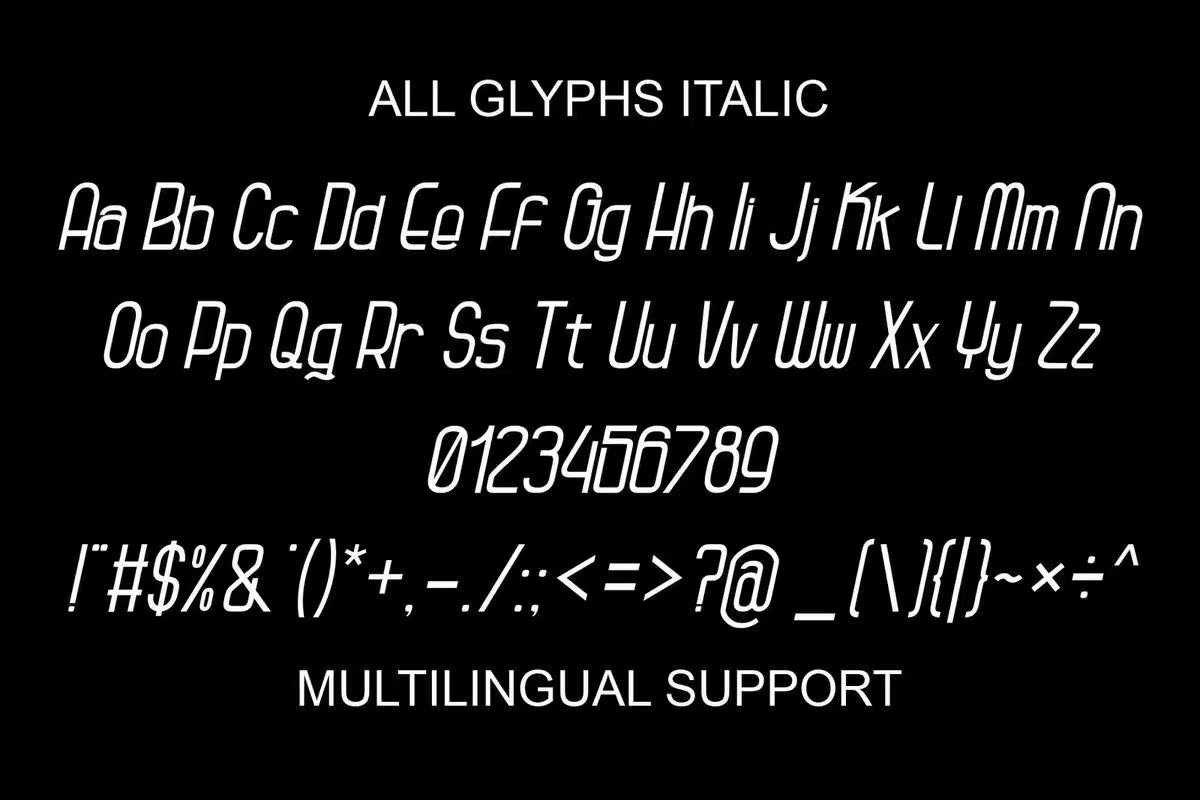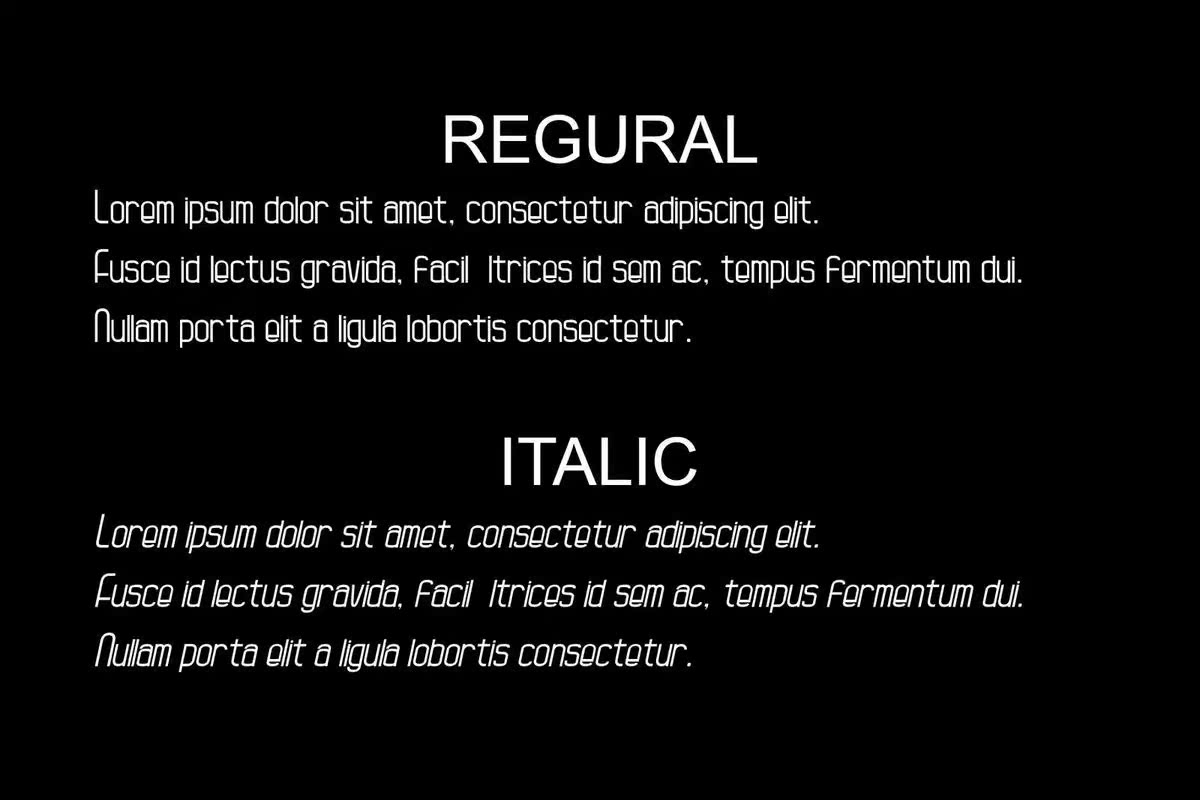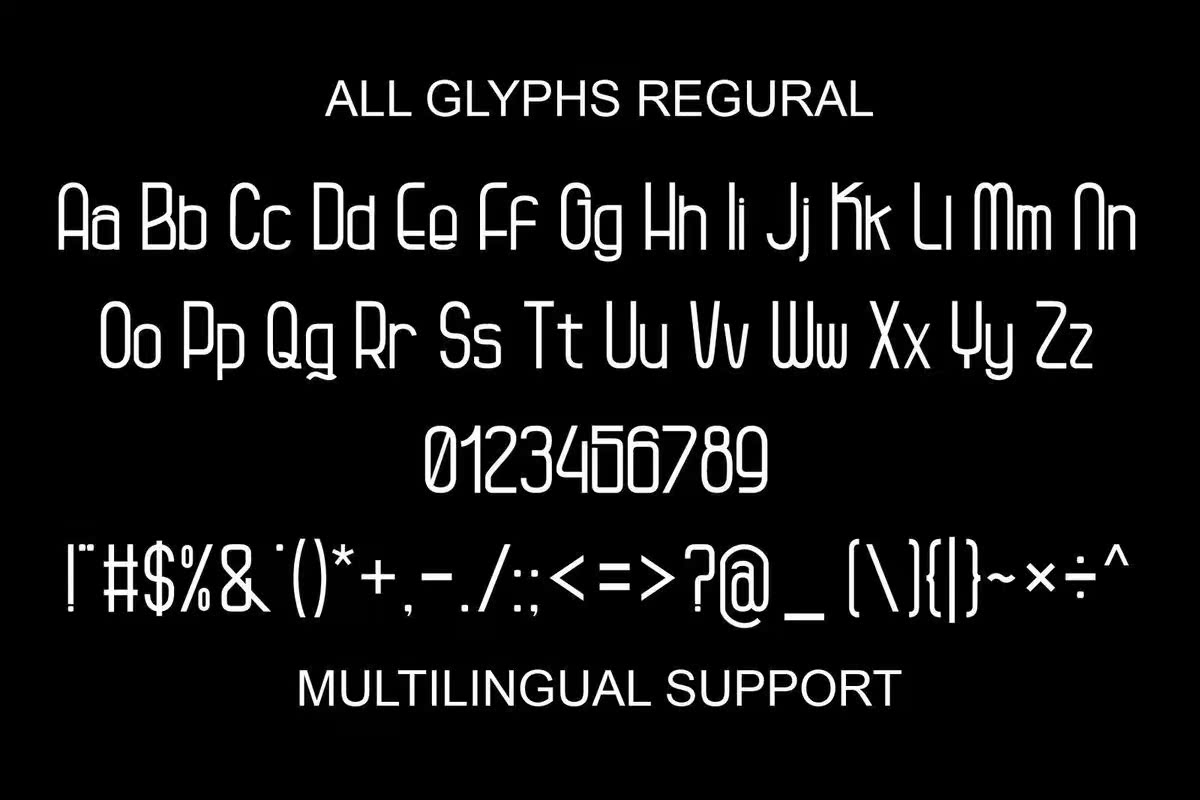
KaguraserifWith Highletter and SexyAppearance。这可用于任何要求愉悦、性感和得体外观的设计。适用于各种项目,包括徽标和品牌、posterdesign、flyerdesign、社交媒体、广告和产品设计。KaguraserifWith Highletter and SexyAppearance。这可用于任何要求愉悦的设计,六、外观设计。适用于各种项目,包括徽标和品牌、posterdesign、flyerdesign、社交媒体、广告和产品设计。